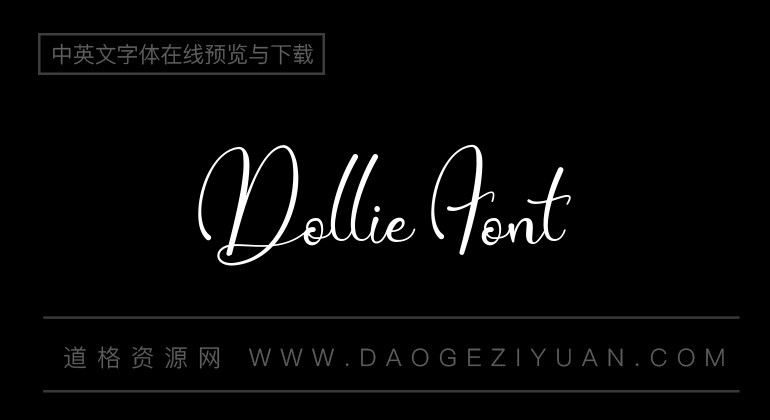
Dollie Font
Dollie Font 是一种华丽的手写字体,它具有一种优雅的女性气质。该字体由美国字体设计师 Sabrina Lopez 创作,适用于多种设计项目,如卡片、海报、书籍封面等。 Dollie Font 包含大写字母、小写字母、数字和标点符号。它的特点是弯曲和连续的线条,使得每个字母都具有一种流畅的感觉。同时,该字体的线条也十分细腻,使得它看起来非常精致。 Dollie Font 可以用于各种不同的场合。例如,在婚礼邀请卡上使用该字体可以使得整个卡片具有一种浪漫的感觉;在书籍封面上使用该字体可以使得整本书看起来更加精致,吸引读者;在海报或广告上使用该字体可以使得产品或事件看起来更有品位。 总之,Dollie Font 是一种非常适合用于女性设计项目的华丽、流畅的手写字体。
Dollie Font是一款非常不错的手写艺术字体,具有很好的视觉感,适合于文化类的宣传设计、商业类品牌的广告和产品包装设计以及个性化文字排版等较多场景。